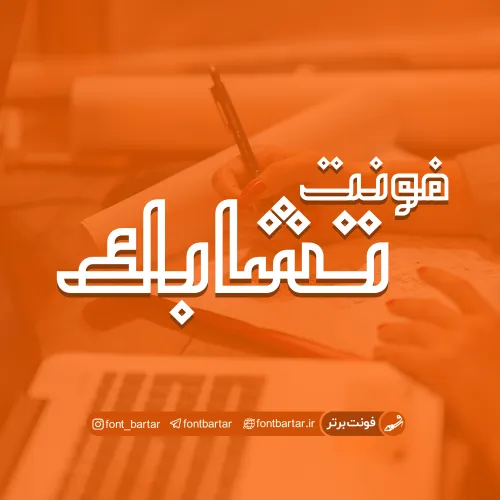
فونت فارسی تشابک
فونت فارسی تشابک  – Tashabok Arabic Font یک قلم بسیار زیبایی است که از آن می‌توان در تایپوگرافی و کالیگرافی طرح‌های مذهبی استفاده نمود. فونت فارسی تشابک در قالب یک فایل otf بر روی سایت قرار گرفته است که پس از نصب آن در پوشه فونت‌های سیستم می‌توانید از آن در طرح‌های گرافیکی خود استفاده کنید.
برخی از حروف و کاراکترهای این فونت را می‌بایست از طریق Glyphs به متون خود اضافه کنید. فونت Tashabok در وزن معمولی (Regular) ایجاد شده است که از آن می‌توانید در طراحی انواع بنر، پوستر، تراکت، کارت ویزیت، بروشور و … استفاده کنید.